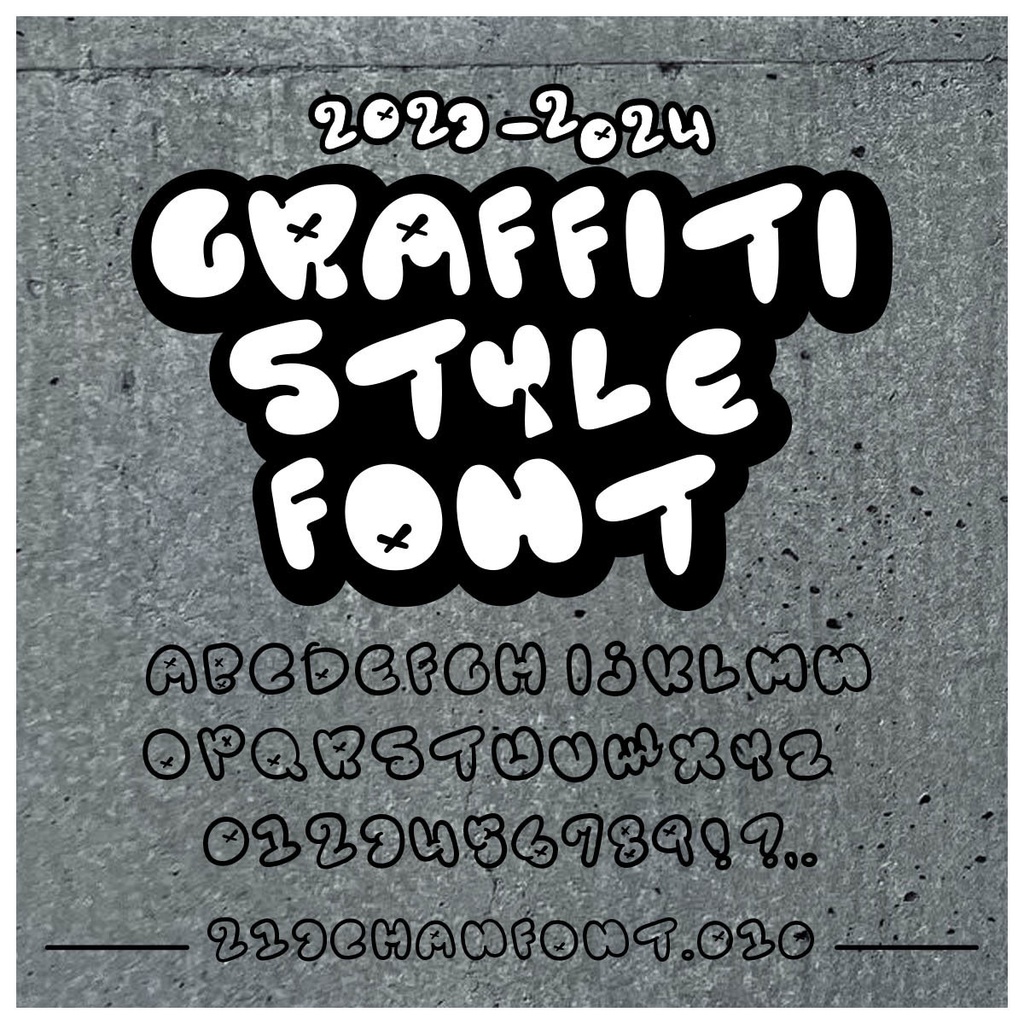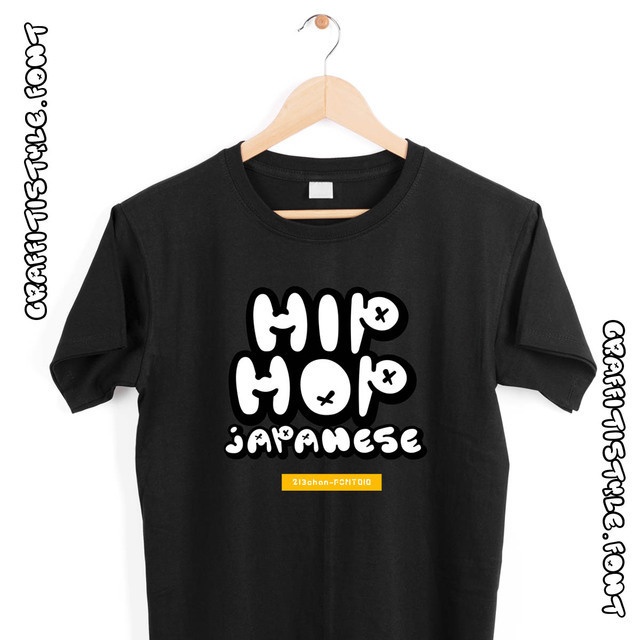
graffitistyel_font(グラフィティスタイル)【商用可】
この213chanフォントは213ちゃんが作った10個目 商用可のフリーフォント(freefont)です。 大文字のみのグラフィティ風フォントです。ペケペケしていて かわいい表情をもっているのでTシャツやグッズにおすすめ。 印刷物・ゲームやWeb、YouTubeのサムネイルやタイトルデザインなどにいかがでしょうか? 基本フリーですが、当フォントを利用した制作物などを、SNSで教えてくれると励みになります。 制作時のお気に入りポイントをnoteで記事にしています。 ぜひ遊びにきてね!スキ!お待ちしています。 https://note.com/sweet_2727/n/n9d7a7497db3d 【収録内容】アルフファベット(大文字)・少しの記号 【Readme】フォントご使用上の注意 ・フォントの著作権は、213ちゃんに帰属します。 ・可愛がってくださるとうれしいです。 ・無断転載・再配布は堅くお断りいたします。 ・DLしたフォントに起因する損害は補償致しかねますので予めご了承ください。 ・使用する際の不明点はお問い合わせ先にご連絡ください。答えられる範囲でお返事いたします。